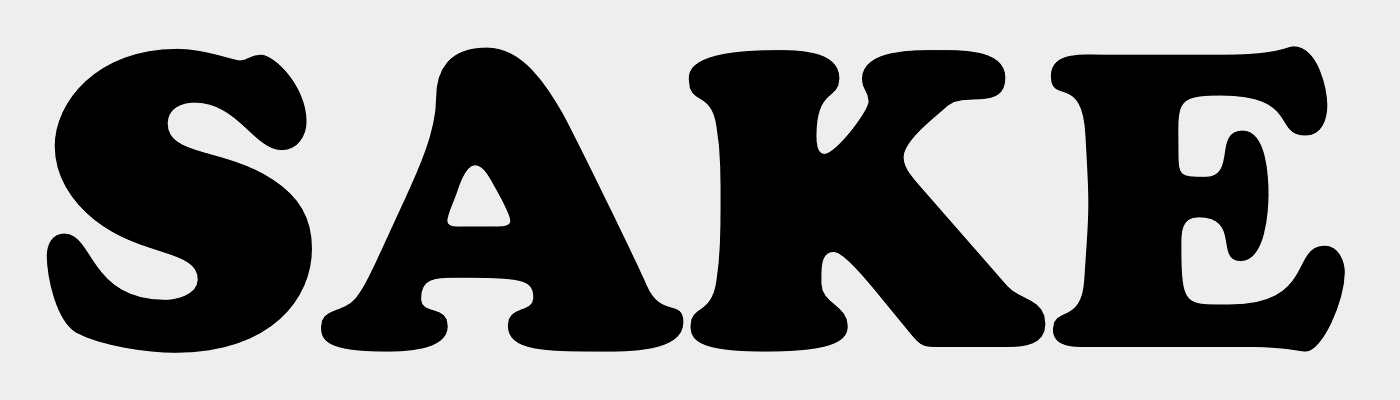
Suche Schrift einer Japanischen Sake Etikette
Ich suche diese Schrift, oder etwas das in die Richtung geht.
Die Font ist von einer alten Suishin-Sake Flasche.
Nun, erst einmal wäre es nicht die Font, sondern der, aber hier ist es gar keiner, sondern eine handgezeichnete Schrift-Grafik. Hier sehe ich 3 mal den Buchstaben A, keines der A gleicht einem anderen, das Gleiche bei den 3 E und auch den beiden S.
Hm, Suishin finde ich nur mit japanischem Etikett (醉心). Vielleicht mal ein Bild im Zusammenhang?
Edit: Hab's jetzt gefunden. Ich denke, du kannst davon ausgehen, dass das handgemacht ist.